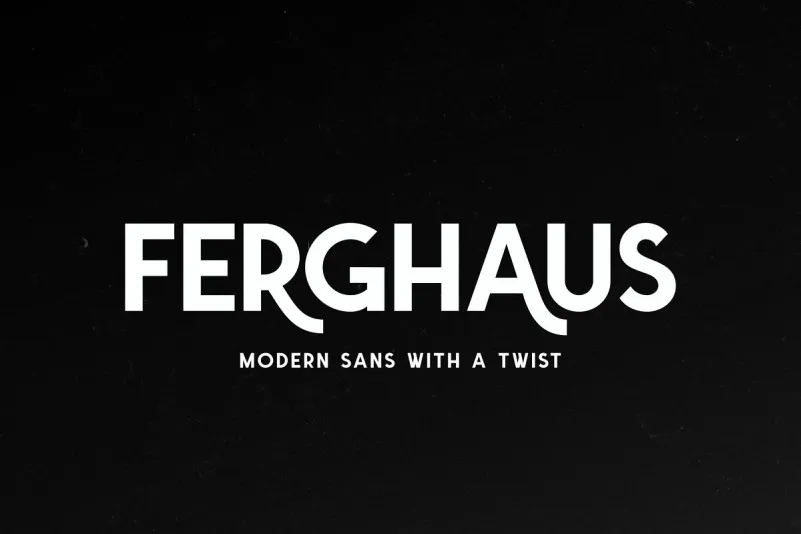
A Ferghaus Sans Font é uma moderna tipografia sans serif projetada para facilitar a leitura e permitir uma boa acessibilidade. As letras são cuidadosamente planejadas para maximizar a legibilidade, oferecendo um design extremamente detalhado que cria um aspecto limpo e ágil em seus trabalhos de design. Esta fonte em maiúsculas é perfeitamente adaptada para todos os tipos de projetos, seja você um designer clássico ou modernista. Ela vem repleta de recursos OpenType como alternativas de caracteres, swashes e ligaturas, tudo isso com o objetivo de permitir que você explore infinitas possibilidades criativas ao combinar as letras. A Ferghaus é altamente versátil e está perfeitamente adaptada para quase qualquer tipo de projeto. Este design do Designer zziplex se destaca pela sua atenção aos detalhes, tornando-se uma fonte ideal para quem busca tanto a elegância quanto a funcionalidade em suas criações visuais.